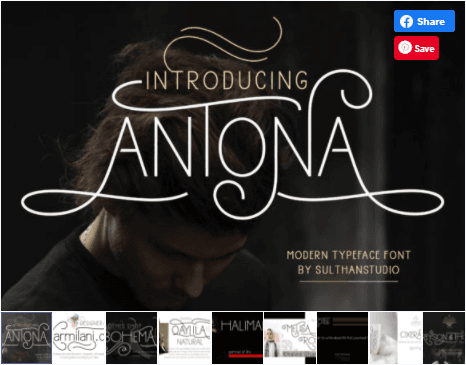
Antona Font
Antona - это элегантный шрифт без засечек с тонкими буквами. Он закодирован в кодировке PUA, что означает, что вы можете легко получить доступ ко всем глифам и росчеркам! Влюбитесь в его невероятно универсальный стиль и используйте его для создания впечатляющих дизайнов!